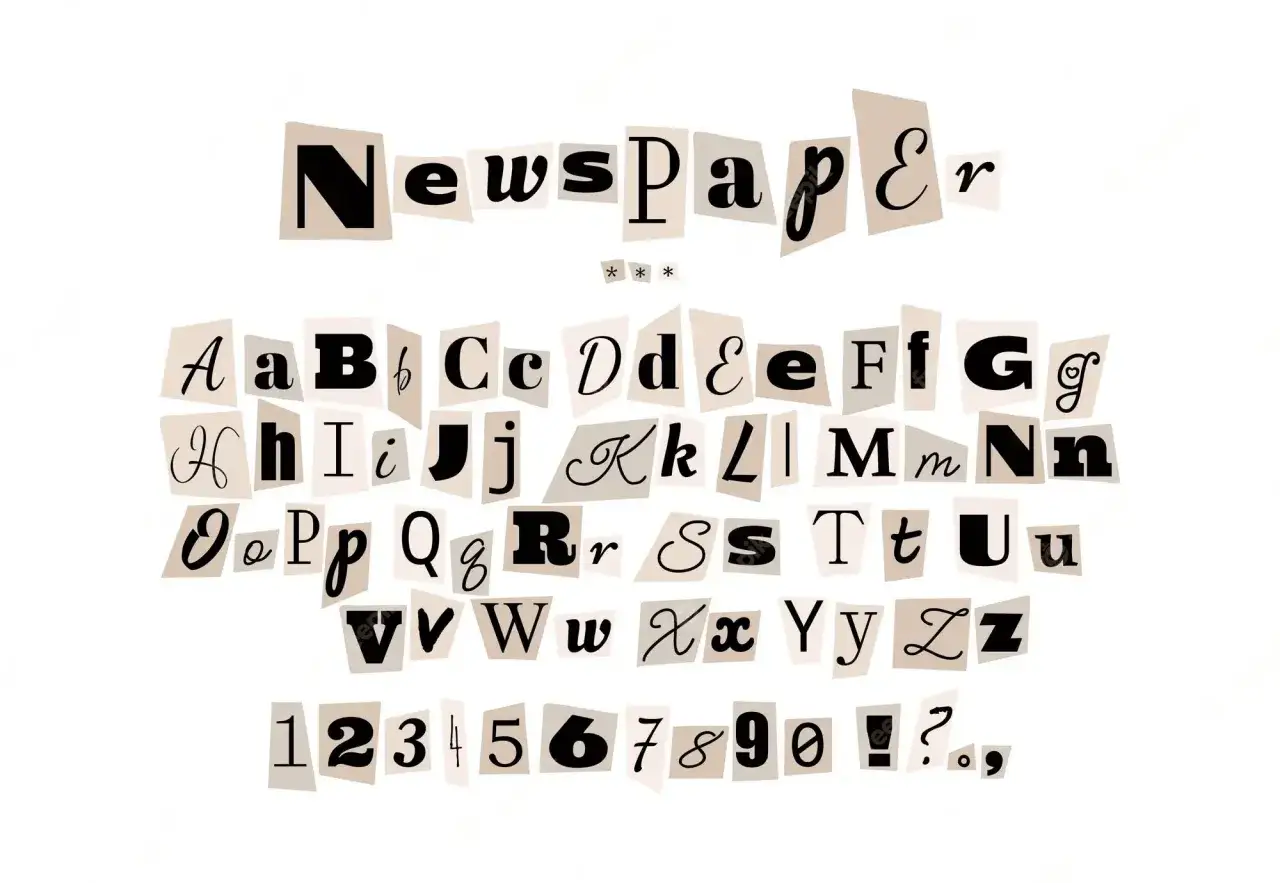
Krój pisma w gazecie - Jak typografia wpływa na czytelność?
Nowoczesna czcionka gazetowa z literami A, B, C, D i pełnym alfabetem.
W prasie drukowanej nie chodzi o jeden ładny font, tylko o cały system czytelności: krój pisma, wielkość, interlinię, szerokość kolumny i hierarchię nagłówków. Czcionka gazetowa to potoczne określenie stylistyki, która ma pozwolić na szybki odczyt w wąskich szpaltach, a jednocześnie zachować porządek informacji i redakcyjny charakter strony. Poniżej pokazuję, z czego ten efekt się bierze, jakie kroje rzeczywiście sprawdzają się w druku i gdzie najłatwiej popełnić błąd.
W gazecie liczy się nie sam font, lecz to, jak pracuje w kolumnie
• Gazetowy skład opiera się na czytelności, a nie na dekoracyjności.
• W dłuższych tekstach najczęściej wygrywają kroje szeryfowe, bo prowadzą wzrok po wierszu.
• W praktyce dobrze działają wielkości rzędu 9-10 pt dla tekstu głównego, z interlinią około 1,4-1,5.
• Jedna rodzina kroju zwykle nie wystarcza, ale więcej niż dwa fonty w jednym materiale to już ryzyko chaosu.
• Na efekt końcowy mocno wpływają też papier, jakość druku, szerokość kolumny i podział wyrazów.
Jak rozumieć gazetowy krój pisma
W praktyce nie mówimy o jednym, sztywnym wzorze. Gazetowy krój pisma to raczej zestaw decyzji typograficznych, które razem mają dać szybki, bezwysiłkowy odczyt: odpowiedni krój, właściwa wielkość, spokojny rytm liter i sensowna hierarchia elementów. Dlatego w redakcji patrzę na tekst nie jak na pojedynczą czcionkę, ale jak na cały układ, który musi działać w wąskiej kolumnie, często pod presją miejsca.
Warto też rozróżnić pojęcia. Krój pisma to zaprojektowany zestaw znaków, font jest jego cyfrową wersją, a sama „czcionka” to termin starszy, drukarski. To nie jest akademicki detal dla zasady, bo precyzyjne nazwanie narzędzia pomaga szybciej dobrać rozwiązanie do konkretnego zadania, zwłaszcza gdy przygotowuje się gazety, biuletyny albo materiały informacyjne dla biura.
Jeśli mam wskazać sedno, to w prasie najpierw wygrywa funkcja, a dopiero potem charakter. Ten porządek prowadzi nas prosto do źródeł formy liter, czyli do kaligrafii i jej wpływu na współczesny druk.
Litery i cyfry wycięte z gazety tworzą napis
Kaligraficzny rodowód, który wciąż działa w druku
Dzisiejsze kroje prasowe bardzo często czerpią z kaligraficznego sposobu prowadzenia linii. Szeryfy, czyli drobne zakończenia znaków, nie są wyłącznie ozdobą. W dłuższym tekście działają jak wizualne zaczepy, które pomagają oku płynąć po wierszu i szybciej rozpoznawać rytm słów. To właśnie dlatego w druku tak dobrze sprawdzają się rodziny o umiarkowanym kontraście, z otwartymi wnętrzami liter i wyraźnym kształtem znaków.
W praktyce lubię patrzeć na trzy cechy. Po pierwsze, otwarte światła, czyli przestrzenie wewnątrz liter, bo litera zbyt zamknięta zaczyna się zlewać w małym stopniu pisma. Po drugie, wysokość x, czyli wysokość małych liter bez wydłużeń, bo większa wysokość x zwykle poprawia czytelność w małych rozmiarach. Po trzecie, umiarkowany kontrast kreski, bo cienkie włoski na słabym papierze potrafią po prostu zniknąć.
Nie każdy serif działa tak samo. Krój o zbyt dużym kontraście wygląda elegancko w nagłówku, ale w kolumnie gazety może być kapryśny. Z kolei slab serif, czyli odmiana z grubszymi, prostszymi szeryfami, bywa bardzo użyteczna w materiałach, które mają wyglądać „prasowo”, ale jednocześnie wytrzymać gorszy papier i szybszy druk. Z tego rodzi się praktyczny wybór rodzin, które naprawdę trafiają do prasy.
Jakie kroje najczęściej trafiają do gazety
W redakcyjnym składzie zwykle nie szuka się jednej idealnej rodziny, tylko kilku ról do obsadzenia. Inny krój prowadzi długi artykuł, inny ma wyciągnąć tytuł, a jeszcze inny ma uspokoić podpis pod zdjęciem. Poniżej pokazuję, jak patrzę na te funkcje w praktyce.
Element Jakiego kroju potrzebuje Po co to działa Przykładowy kierunek
Tekst główny Spokojny, czytelny, z umiarkowanym kontrastem i otwartymi znakami Ma dawać płynne czytanie bez zmęczenia Rodzina szeryfowa typu Times, Georgia, Minion, Charter, Source Serif
Lead Trochę mocniejszy lub bardziej kompaktowy niż tekst główny Ma oddzielić wstęp od korpusu i przyciągnąć wzrok Bold tej samej rodziny albo lekko skondensowany wariant
Nagłówek Wyrazisty, cięższy, często bezszeryfowy albo skondensowany Ma zbudować hierarchię i zrobić miejsce dla szybkiego skanowania Helvetica, Arial, Franklin Gothic, Akzidenz-Grotesk, Roboto Condensed
Podpis pod zdjęciem Prosty, neutralny, zwykle mniejszy od tekstu głównego Nie może konkurować z treścią i zdjęciem Ta sama rodzina co tekst albo prosty sans-serif
Ramka, infografika, notka Jasno odróżniony od tekstu głównego, ale nadal bez przesady Ma pomóc w szybkim skanowaniu i porządkowaniu informacji Wersja pogrubiona, bezpieczny sans lub krój o wyższej ekspozycji
W praktyce ograniczam się najczęściej do dwóch rodzin w jednym materiale. Jedna obsługuje korpus tekstu, druga nagłówki i wyróżnienia. To wystarcza, o ile oba kroje są dobrane świadomie, a nie wybrane przypadkiem z listy systemowej. Taka dyscyplina robi większą różnicę niż efektowny, ale nieczytelny font z katalogu.